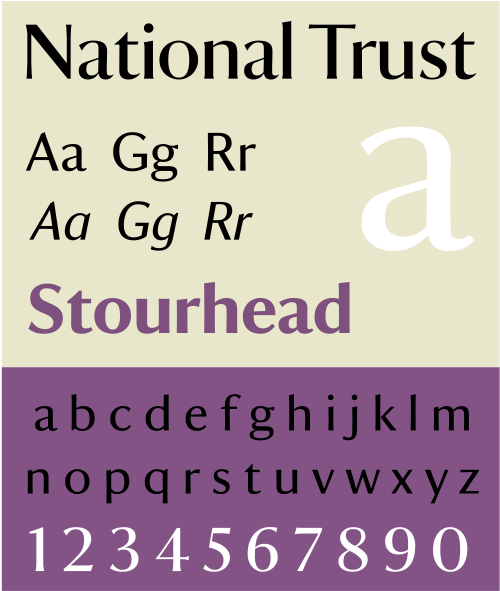
| カテゴリ | サンセリフ |
| 分類 | ヒューマニスト |
| デザイナー | ポール・バーンズ |
ナショナル・トラストは、ポール・バーンズがイングランド、ウェールズ、北アイルランドのナショナル・トラストのためにデザインしたヒューマニスト ・サンセリフ 書体です。 [1] [2]これは企業フォントファミリーであり、ライセンスは利用できません。[3]
ナショナル・トラストのフォントは、1946年以来ナショナル・トラストが一部所有しているストウヘッドの地所に1748年頃に刻まれた碑文に基づいています。[4]このフォントの基になっている碑文は、ニンフの像が眠る湖のほとりの洞窟にある「春のニンフ」というエピグラムで、ほとんどがサンセリフ体で、古代以来このようなスタイルが使用された最初の例の1つです。
この碑文の珍しいスタイルは歴史家たちの注目を集めたが、最も有名なのはジェームズ・モズレーで、モズレーの初期のサンセリフ体に関する著書『ニンフと洞窟』はこの碑文にちなんで名付けられている。 [5] [6] [a]モズレーは、このスタイルの起源は定かではなく、後継者に影響を与えたようには見えないが、その珍しい簡素化された構造は、自然の洞窟を模倣することを意図した建築の精神に関連した「素朴な表現」である可能性があると結論付けている。[5] [8] [9] [10]この碑文は1967年に誤って破壊されたため、モズレーの写真から複製しなければならなかった。[5] [11]
ナショナル・トラストは、ストゥアヘッド碑文に基づいているため、水平方向と垂直方向の線幅が明確に異なる「強調された」または「調整された」サンセリフ体となっている。 [ 12]このスタイルの他の書体には、オプティマ(フィレンツェの中世の碑文に触発された)、ブリタニック、ラディアントなどがある。[13]
この4行詩は、アレクサンダー・ポープによってラテン語から英語に翻訳され、ドナウ川の上の眠るニンフの像がある伝説的なローマの噴水の碑文に由来するとされている。[9] [14] [15]噴水のそばで眠るニンフというモチーフは、ルネサンス時代の人文主義者に人気があり、新古典主義の庭園設計者にも影響を与えたが、現在では15世紀の贋作ではないかと一般に疑われている。[16]英語では、次のようになっている。
洞窟のニンフよ、私はこの神聖な泉を守っている
そしてこの水のささやきを聞きながら眠る ああ
、どうか私の眠りを止めて、そっと洞窟を歩き
そして静かに水を飲んで、あるいは静かに洗って。[17] [18]